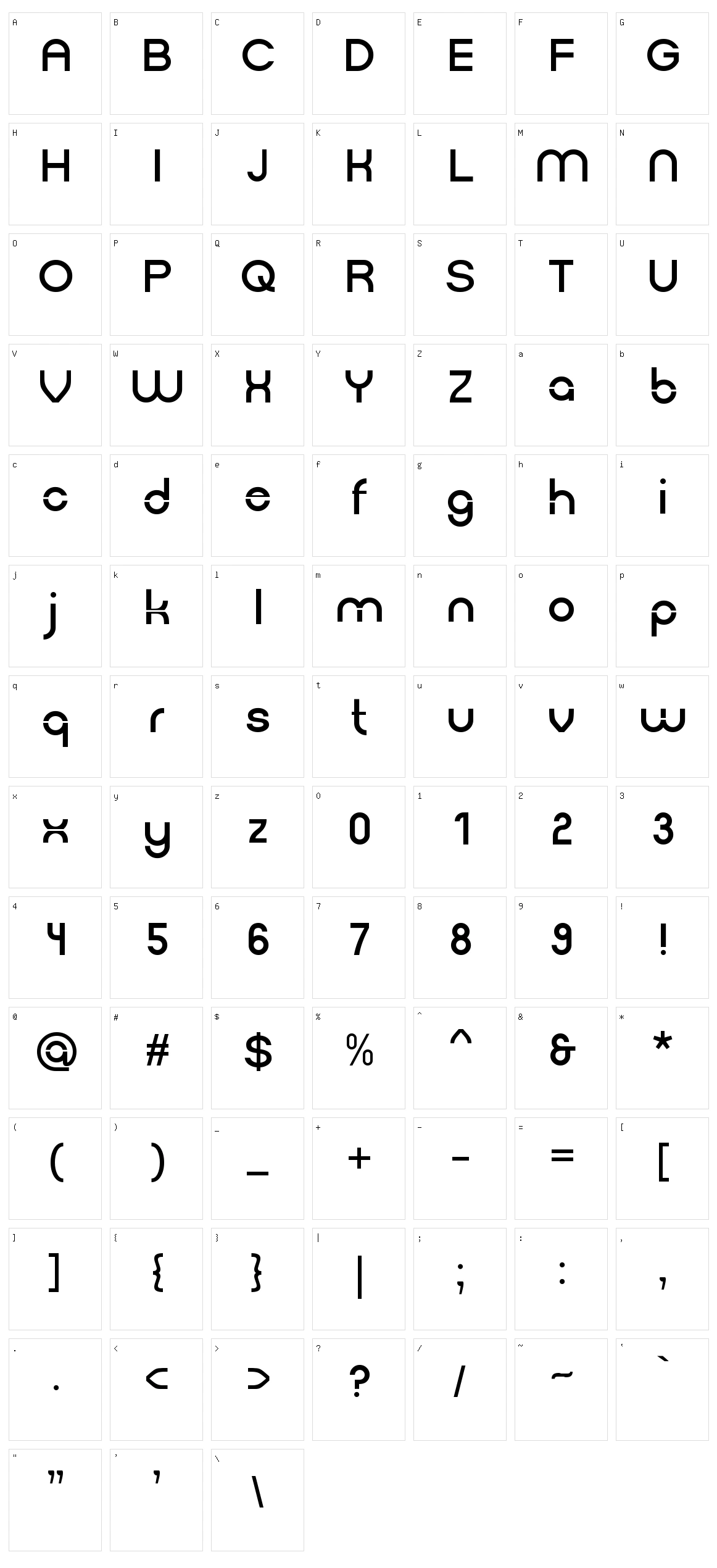
gpkn font adalah font yang didesign, oleh Situjuh Nazara khusus, untuk GPKN (Gerakan Pemuda Kepulauan Nias).
Font ini diguanakan sebagai tulisan pada logo "gpkn" dan media tulisan lainnya yang dikelola oleh GPKN.